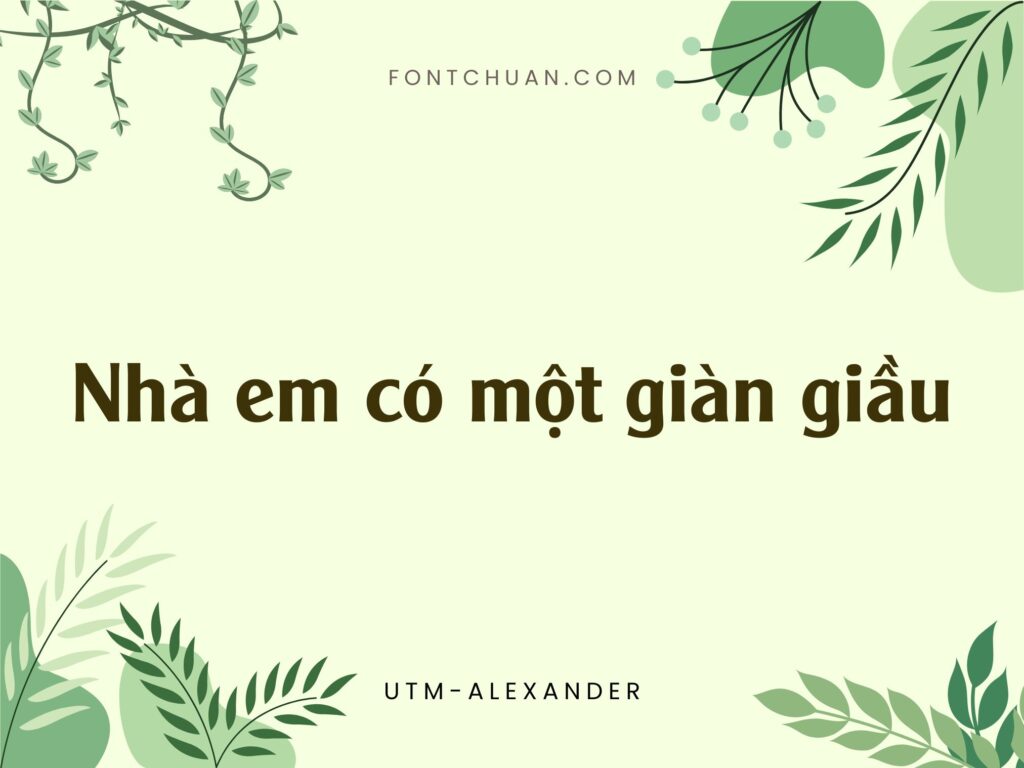
Font UTM Alexander Việt Hóa
UTM Alexander là một kiểu Font Serif cổ điển, được thiết kế bởi George Douros. Phiên bản này đã được Việt hóa, hỗ trợ đầy đủ tiếng Việt cùng hơn 100 ngôn ngữ khác. Thành viên của Font Chuẩn đã sưu tầm và chọn lọc font này nhằm đáp ứng nhu cầu đa dạng của bạn đọc và ứng dụng thực tế vào các dự án thiết kế.
UTM Alexander có cấu trúc chữ với các nét thanh mảnh và chân chữ tinh tế, tạo nên vẻ đẹp trang nhã và lịch sự. Font này phù hợp cho các ứng dụng như thiết kế logo, tiêu đề, bao bì sản phẩm và các ấn phẩm in ấn. Các ngành nghề như quảng cáo, giáo dục, bất động sản và công nghệ có thể tận dụng UTM Alexander để tạo điểm nhấn độc đáo trong thiết kế.